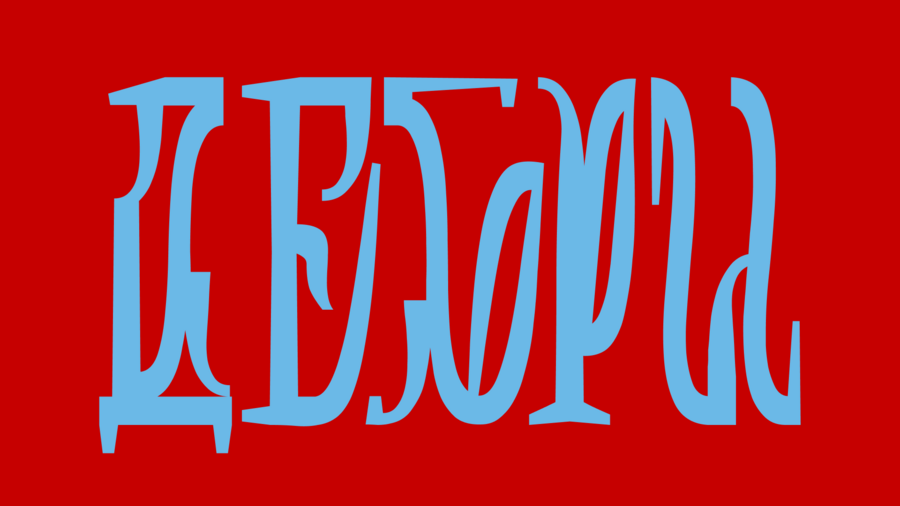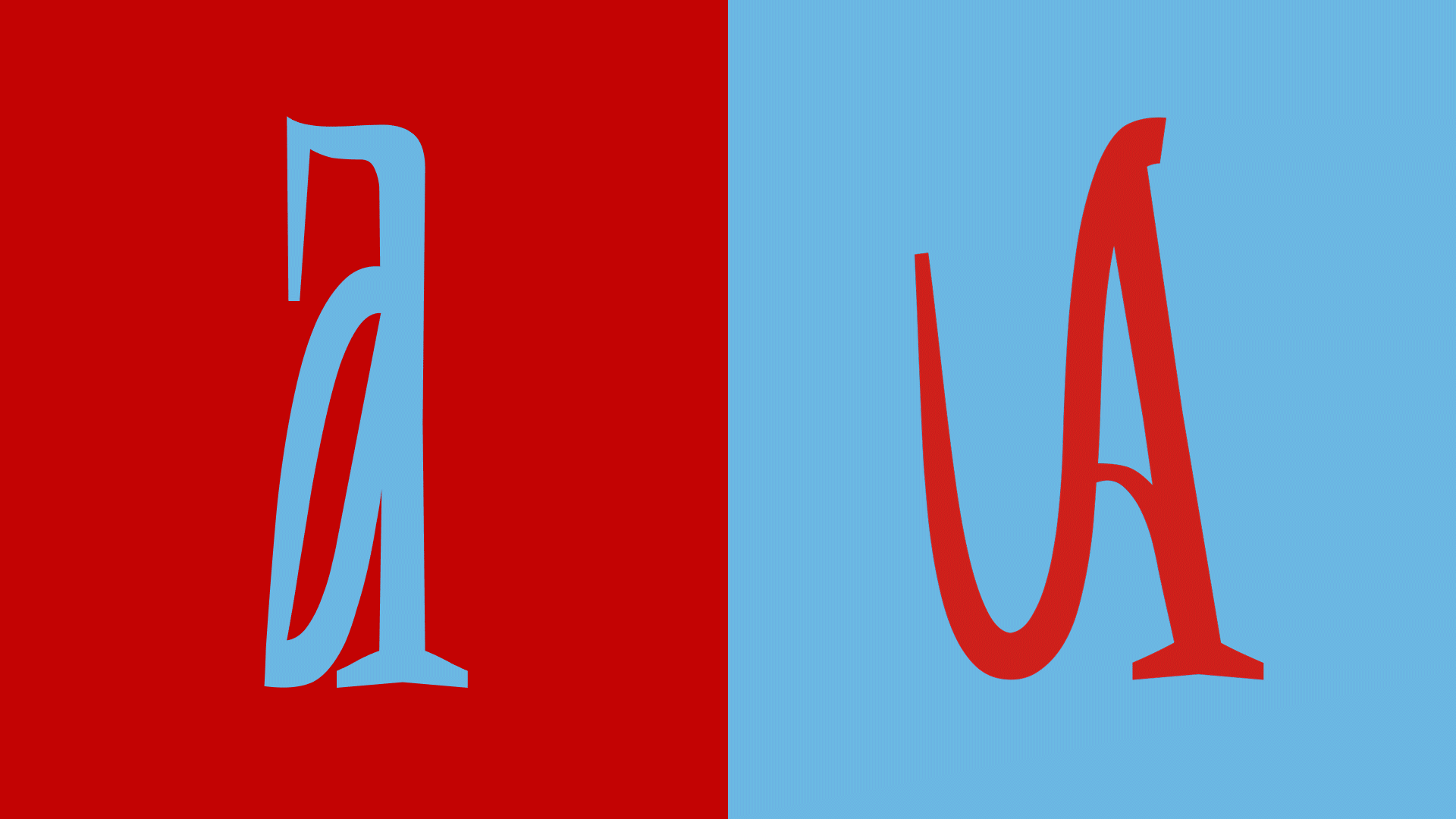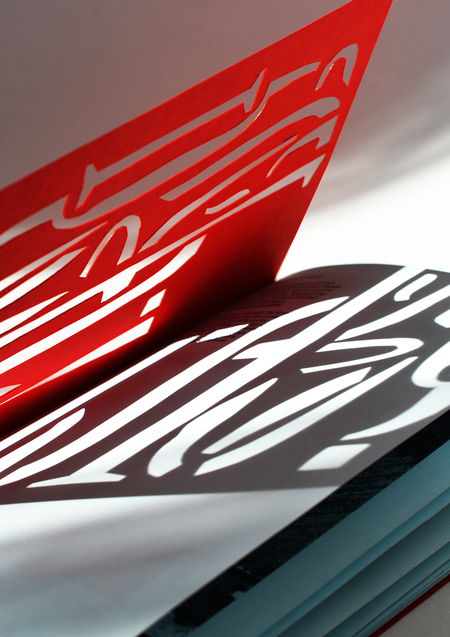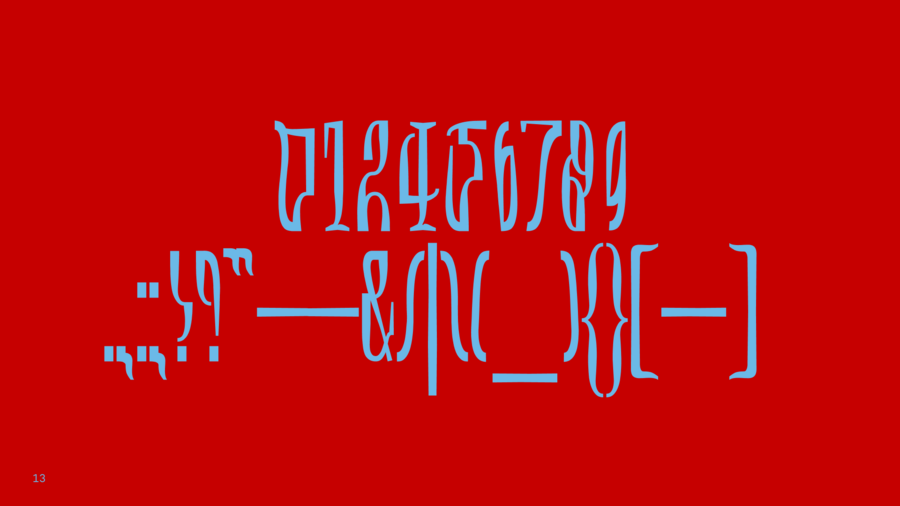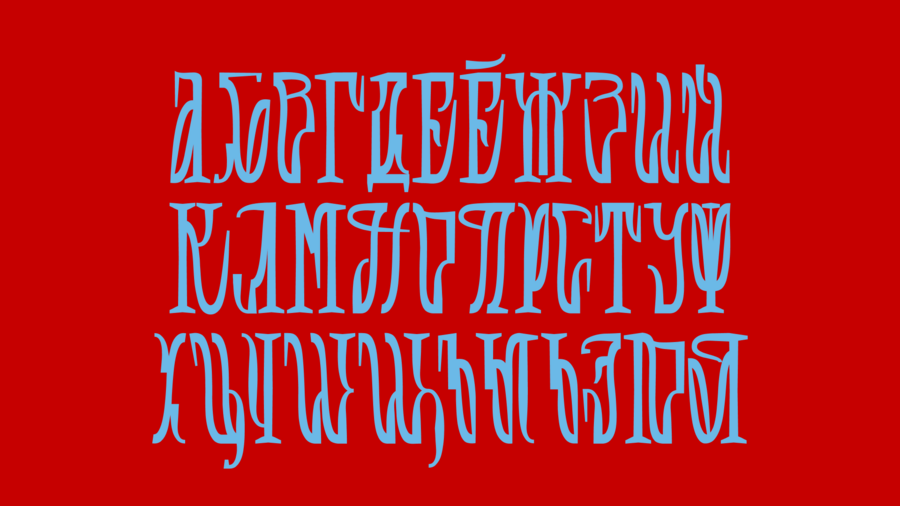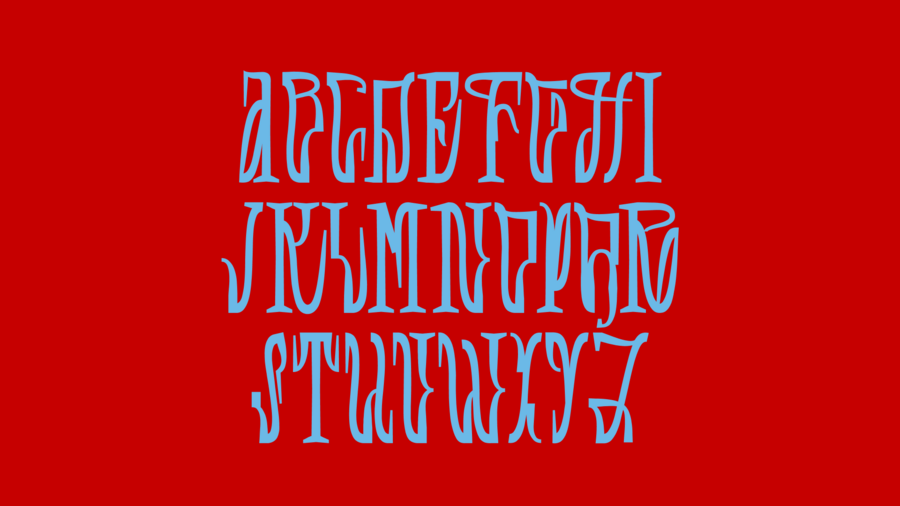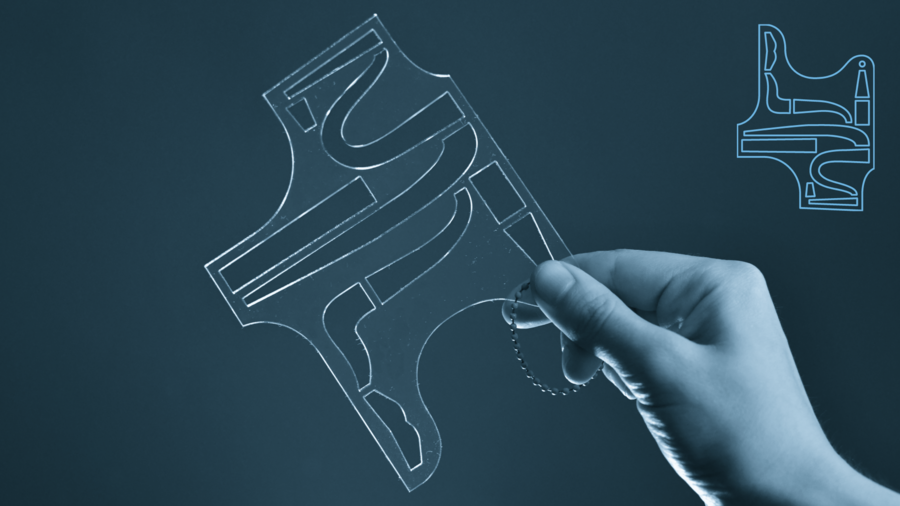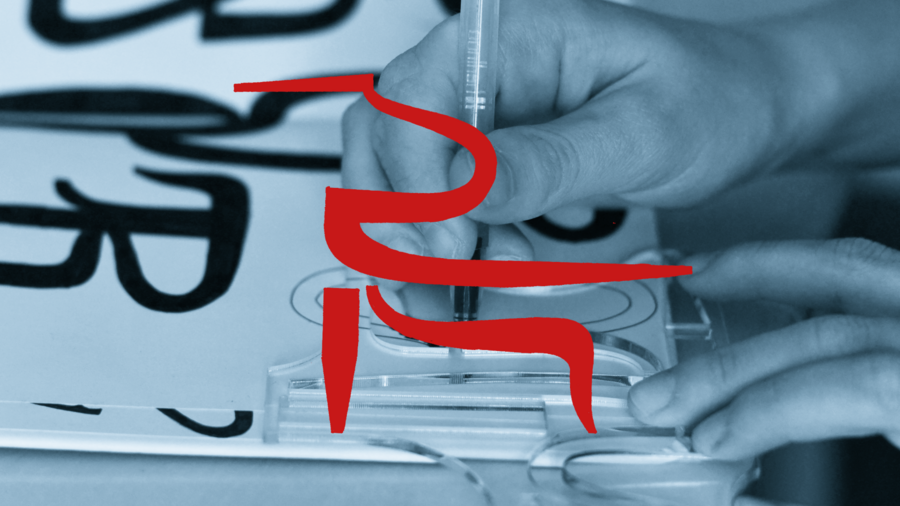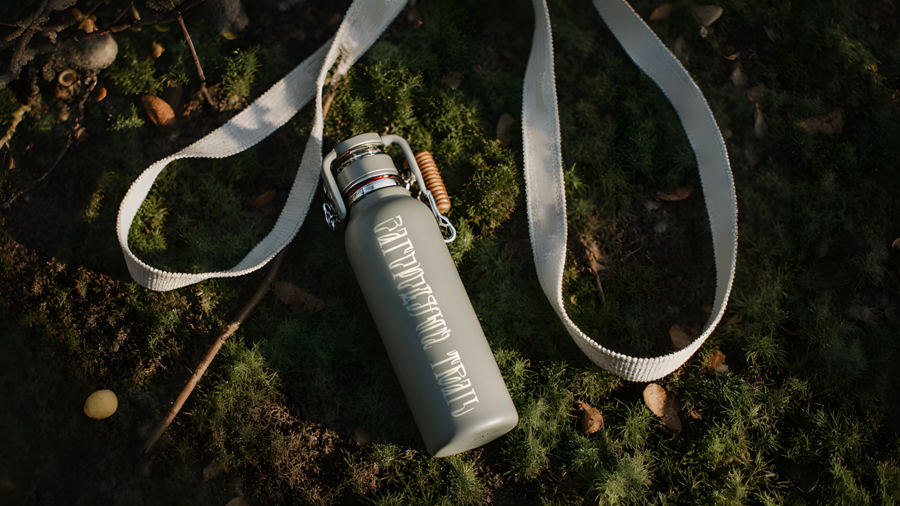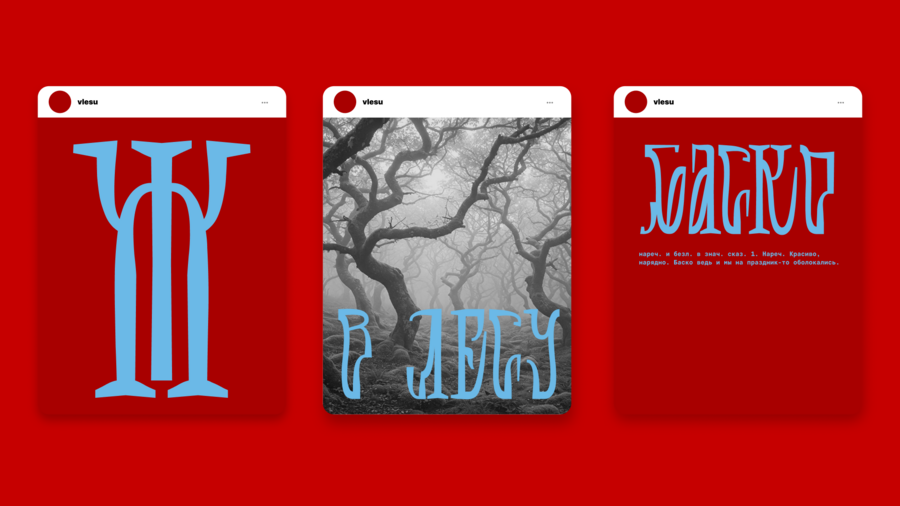
Дебри — модульный шрифт, вдохновлённый старыми деревянными домами в лесу частного сектора в Санкт-Петербурге.
Альтернативные начертания букв
В качестве знака отсутствующего символа появляется пегас, получившийся из рисования с помощью модульной линейки.
Знак notdef и модульная линейка
Шрифт в среде
Зин о шрифте
Обложка с вырезанными буквами создаёт мелькание солнца, как в дебрях
Каждому модулю в зине давно собственное название
Зин предлагает читателю оторвать вставки с модулями и порисовать свой шрифт